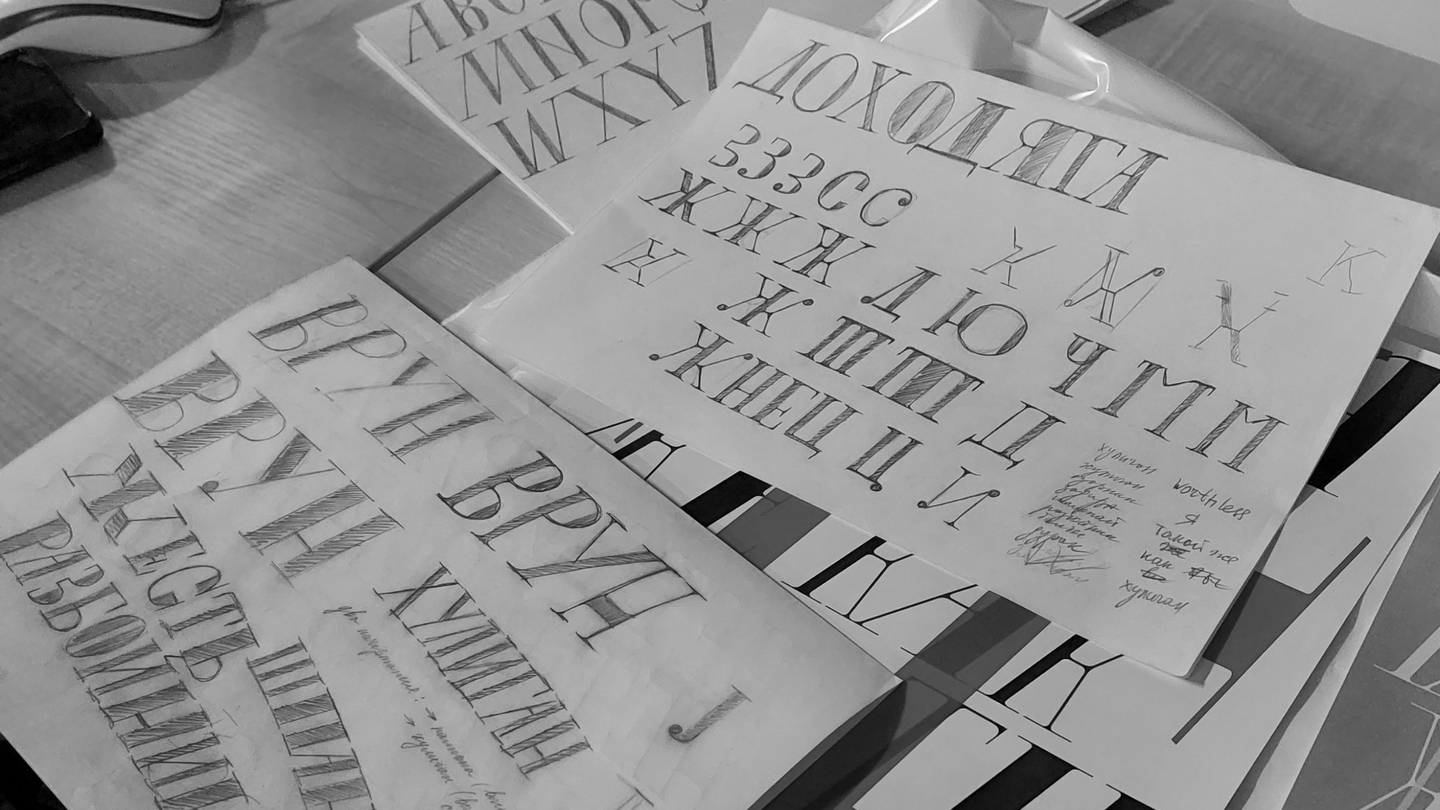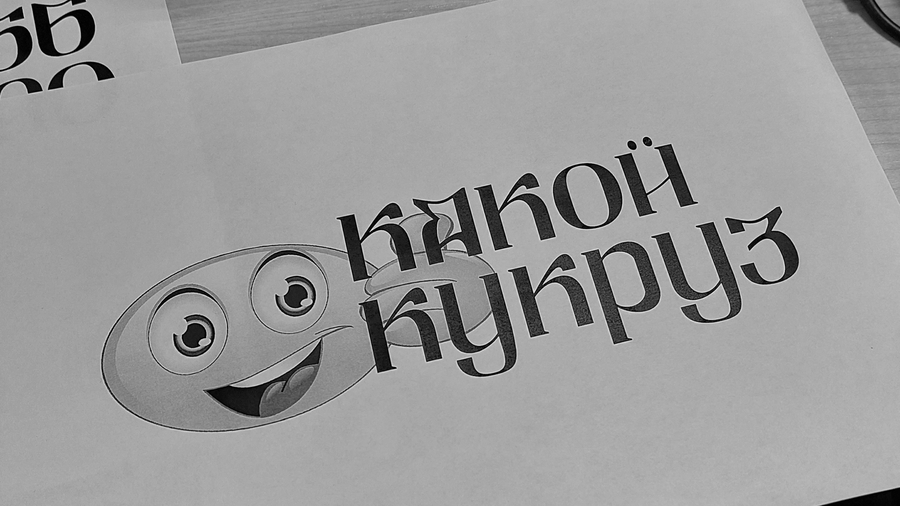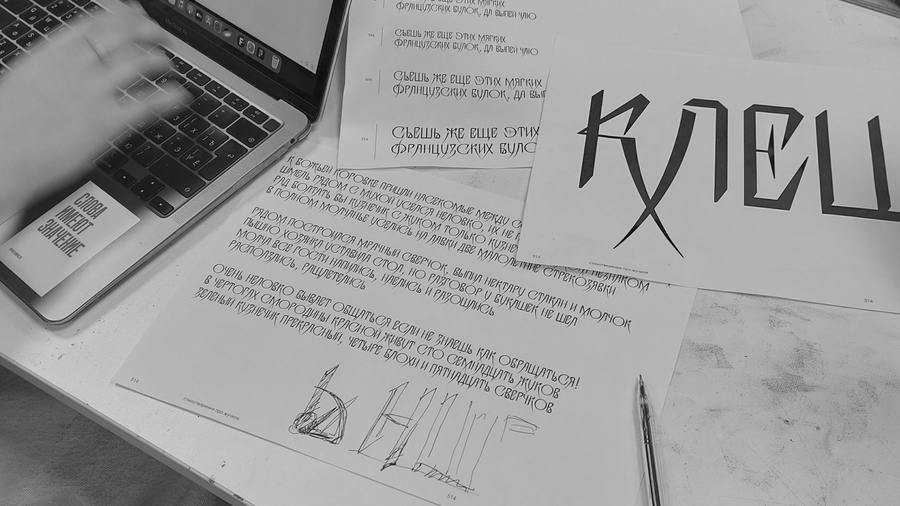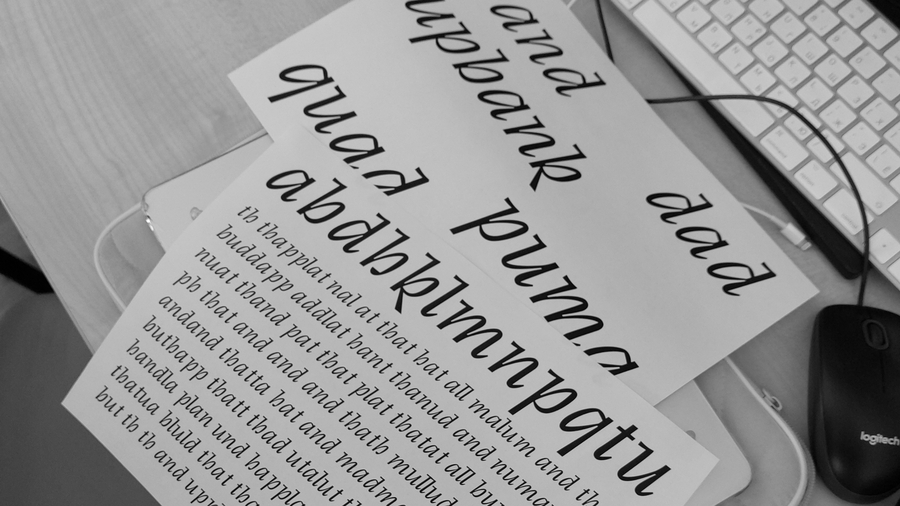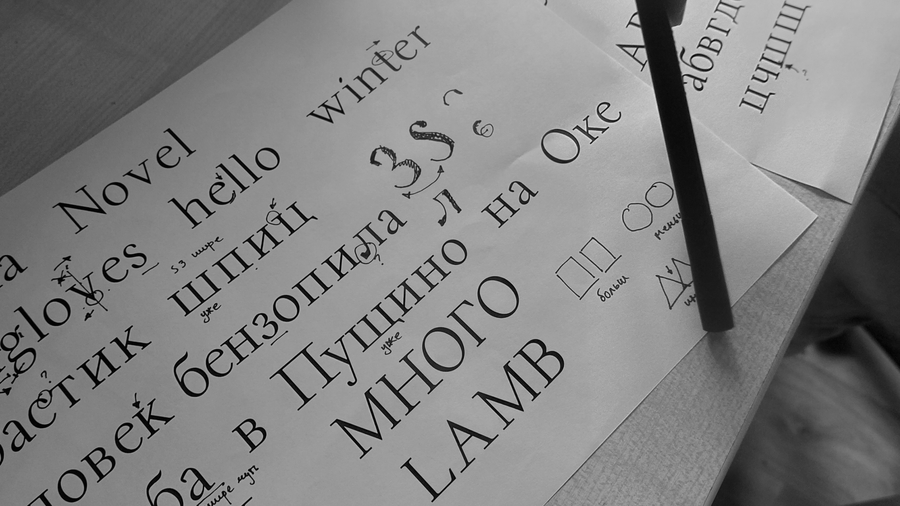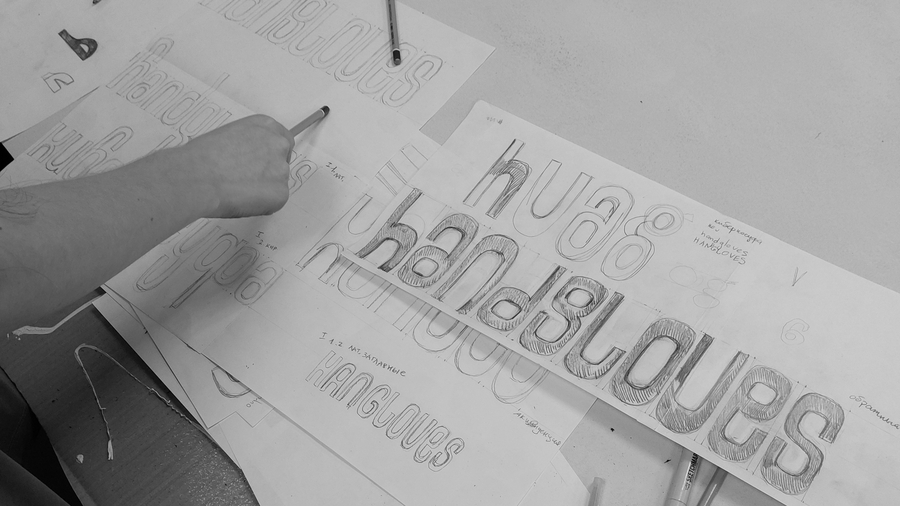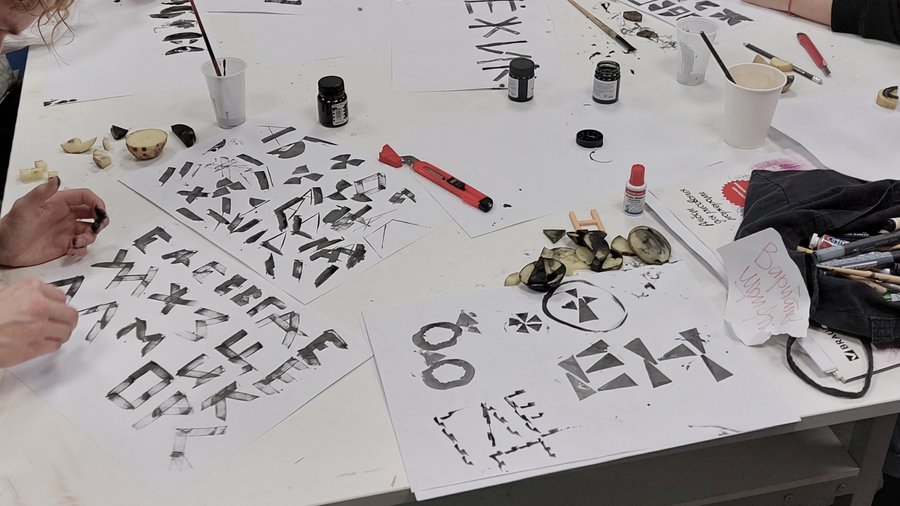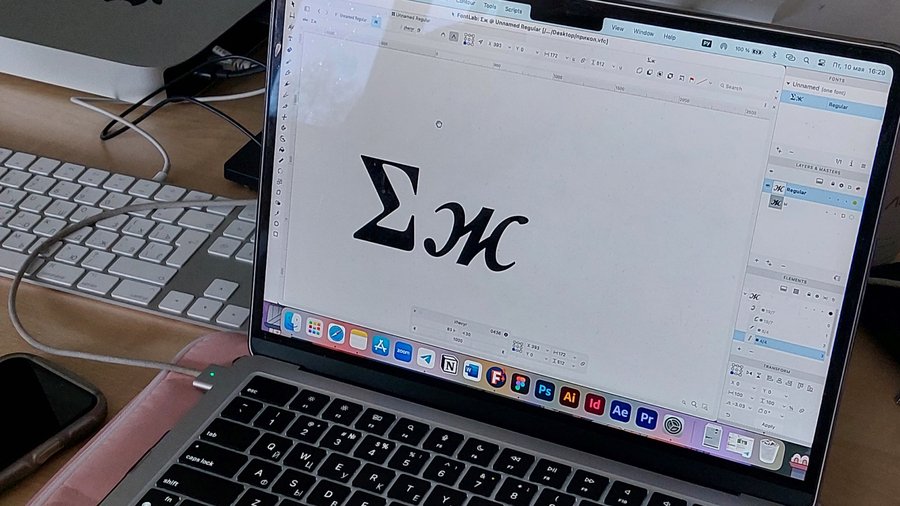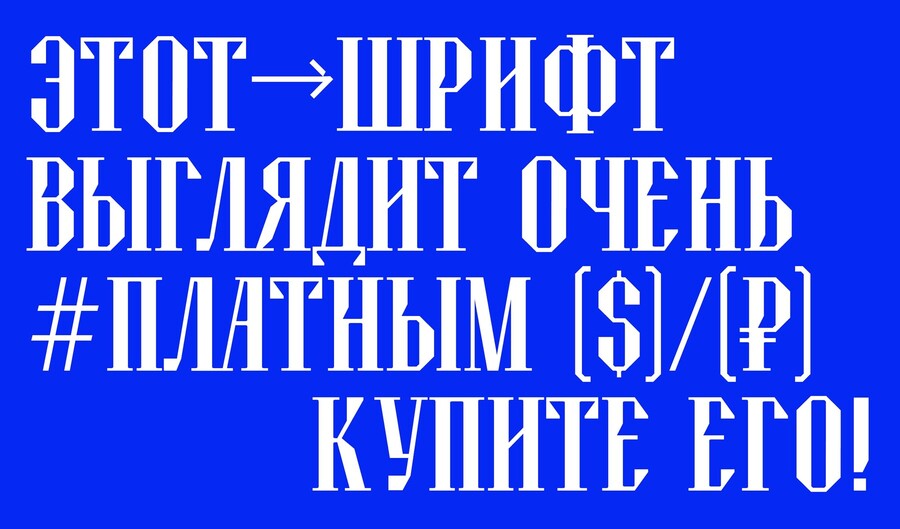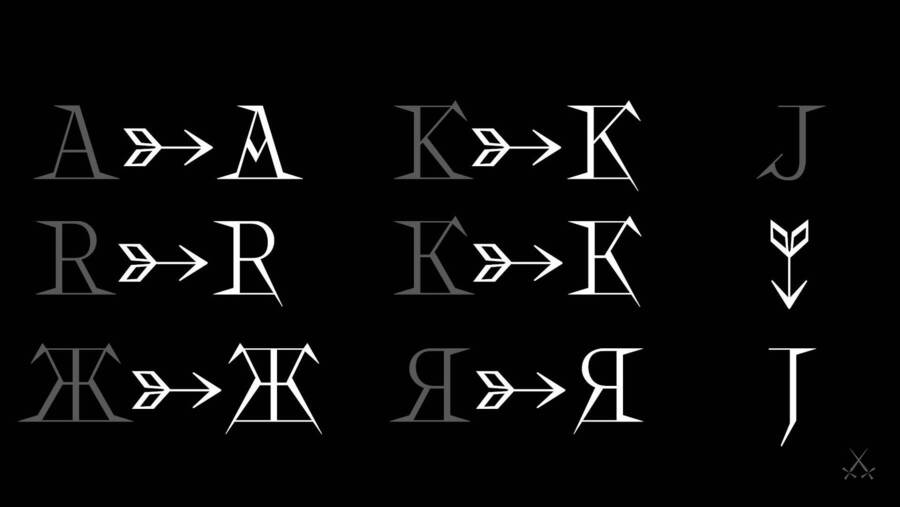
Шрифт
Вариативный курс
Вариатив «Шрифт» знакомит студентов с основами профессии дизайнера шрифтов и позволяет научиться понимать, по каким законам существует шрифт. Курс посвящён различным аспектам дизайна шрифта, и включает в себя как теоретический блок, посвящённый терминологии, эволюции шрифтовых форм и вопросам классификации, так и работы в шрифтовом редакторе.
Чему вы научитесь?
Не просто смотреть на буквы, а видеть их структуру, логику и характер. Эти знания помогут создавать собственные проекты или просто лучше разбираться в типографике.
Основы шрифтового дизайна
Разберёмся, из чего состоит шрифт: от отдельных букв до их взаимодействия в тексте. Мы поговорим о ключевых понятиях, таких как ритм, пропорции и баланс. Научимся видеть закономерности в формах букв и понимать, как они влияют на читаемость и визуальное восприятие текста.
Работа с формой и деталями
На курсе вы освоите базовые принципы работы с формой букв: как строить гармоничные контуры, как работать с толщиной линий и как добиться выразительности в деталях. Мы будем изучать, как мелкие нюансы — например, форма засечек или наклон штрихов — могут менять характер шрифта.
Практика в шрифтовом редакторе
Вы познакомитесь с основами работы в профессиональных шрифтовых редакторах — от первых эскизов до цифровой реализации.
Результатом курса станет готовый шрифтовой файл и презентующие его в реальном использовании материалы
Dilemma. Анжелика Саркисян Gehaks. Эмили Михайленко Rennen. Елизавета Островская
Epistem. Аня Иванова Careerist. София Волкова Антресоль. Анастасия Шабунаева
Итоговые проекты